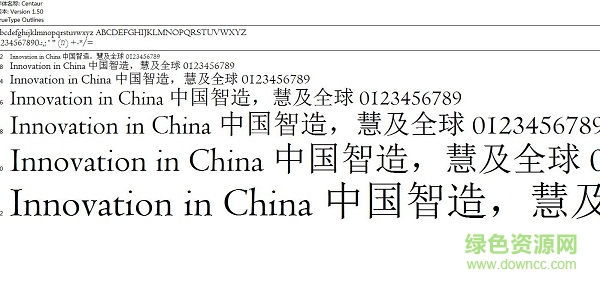
centaur什么字體?centaur字體是一款常常出現(xiàn)在電影海報(bào)中的英文字體,指環(huán)王、霍比特人的海報(bào)就用過(guò)這款字體,大氣恢弘,具有濃重的歷史感,mac系統(tǒng)和Windows系統(tǒng)都可以安裝使用,有需要者歡迎免費(fèi)下載!